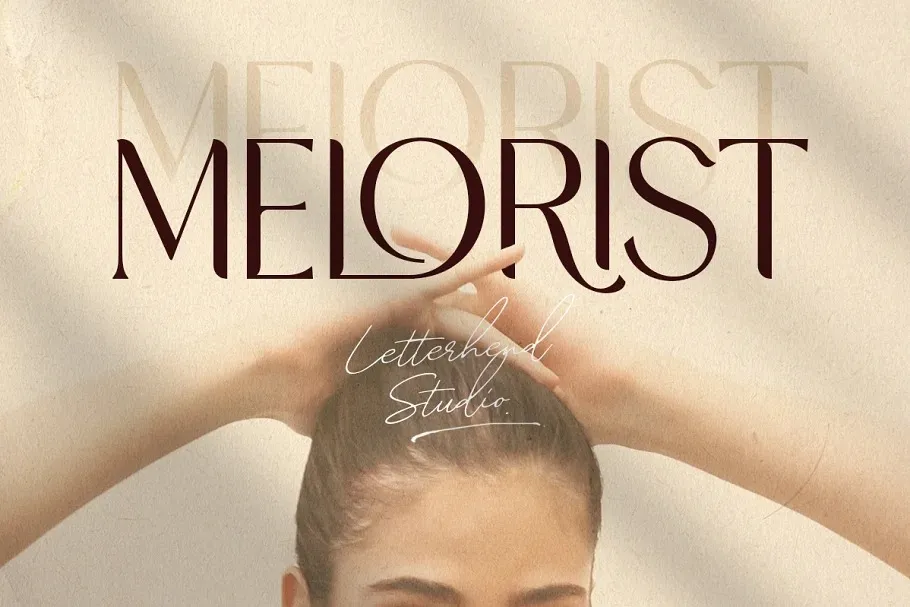
A fonte ‘Melorist Font’ é uma elegante tipografia serifada criada para atender a quem busca modernidade com sabor clássico. Desenvolvida pelo site de criação 99designs, esta fonte traz um toque inconfundível de sofisticação e estilo único aos projetos digitais. Suas alternativas estilizadas e ligaturas diferenciam-a, tornando-a perfeita para aplicações que exijam notoriedade em logotipos, convites, selos, embalagens, livros, cartões de agradecimento, embutidas ou até mesmo anúncios. Com um design cuidadosamente pensado para o uso formal e detalhado, a ‘Melorist Font’ é uma escolha ideal para quem deseja criar identidades digitais que combinem modernidade com elegância clássica.